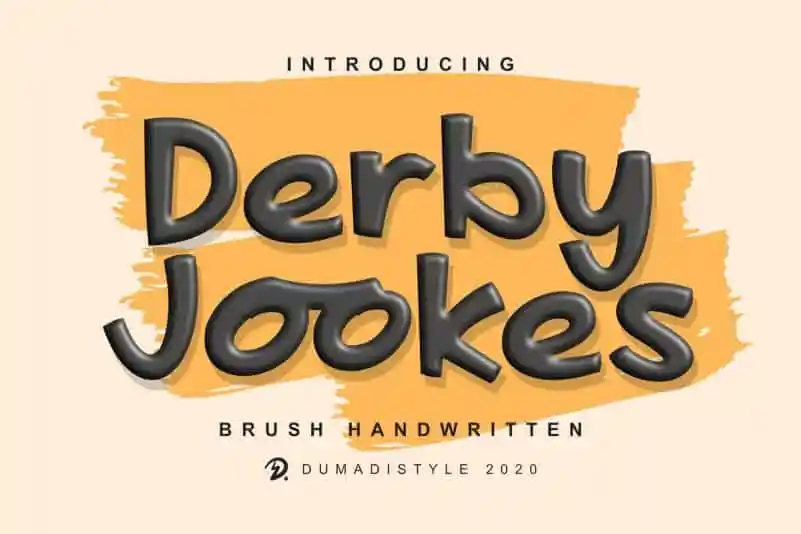
Derby Jookes Display Font – Download Grátis
A fonte ‘Derby Jookes Display Font’ é uma opção brilhante para aqueles que buscam diversão e autenticidade em seu design visual. Embora seja baseada em escrita a mão, esta letra exibe um estilo cartunizado que se destaca por sua simplicidade encantadora. Oferecendo uma linguagem criativa e amigável, o designer DUMADI criou este fonte para designers gráficos apaixonados por designs infantis e cômicos. É perfeito para qualquer tipo de evento, seja um aniversário infantil ou simplesmente criar algo que cause impacto em seu design visual. Escolha ‘Derby Jookes Display Font’ para dar vida a seus projetos criativos de uma maneira única e divertida.